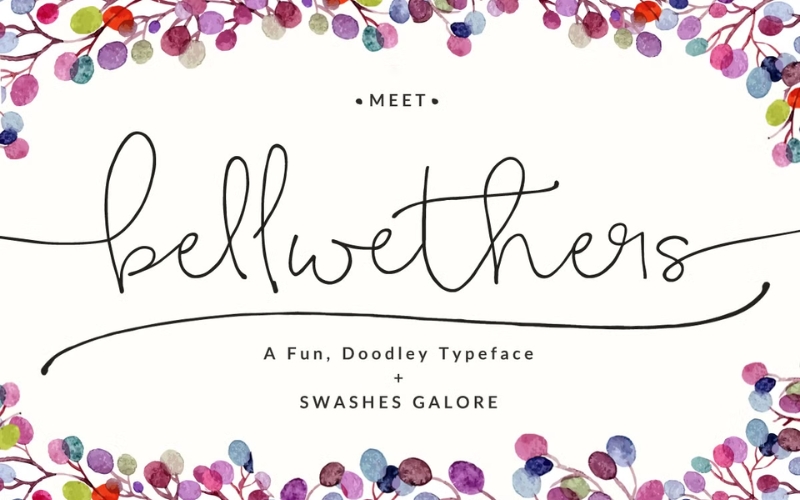
Việc sử dụng các font chữ đẹp và chuẩn Unicode đóng vai trò quan trọng trong thiết kế đồ họa, soạn thảo văn bản hay các ấn phẩm truyền thông. Trong số đó, bộ font SVN Việt hóa được nhiều người ưa chuộng nhờ tính thẩm mỹ cao và khả năng hỗ trợ đầy đủ tiếng Việt. Nếu bạn đang tìm kiếm cách tải font chữ SVN Việt hóa nhanh chóng và an toàn, bài viết dưới đây của Vietkey sẽ cung cấp đầy đủ link download miễn phí cùng hướng dẫn cài đặt chi tiết để bạn có thể sử dụng ngay trên máy tính của mình.
Font SVN Việt hóa là gì?
SVN Font là bộ font chữ đã được Việt hóa bởi một designer vào năm 2013, ban đầu chỉ thực hiện trên một số bộ font nhỏ và chia sẻ miễn phí trong cộng đồng designer. Nhờ sự ủng hộ nhiệt tình từ người dùng, nhu cầu sử dụng các font chữ đẹp, tiện lợi ngày càng tăng, designer này đã tiếp tục Việt hóa thêm nhiều bộ font khác.
Song song với đó, một số mẫu SVN font chất lượng cao được cung cấp dưới dạng dịch vụ trả phí, giúp designer vừa mang đến sản phẩm tốt vừa tạo nguồn thu nhập cá nhân. Những bộ font từ dự án này sau đó được gắn thương hiệu riêng là STYLEno.1 Fonts và nhận được sự tin tưởng, hài lòng từ đông đảo cộng đồng người dùng.
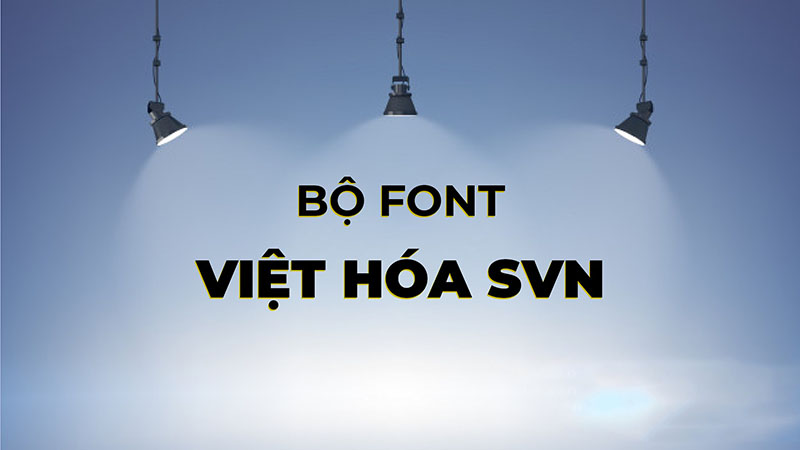
Tất cả các bộ font SVN Việt hóa đều sử dụng bảng mã Unicode phổ biến, đảm bảo khả năng tương thích cao với mọi phần mềm và thiết bị. STYLEno.1 Fonts phân chia SVN Font thành 5 nhóm chính gồm Script, Brush+Handwriting, Sans-serif, Serif+Slab và Others, mỗi nhóm mang đặc trưng riêng phù hợp với nhiều mục đích sử dụng khác nhau. Nếu bạn muốn sở hữu trọn bộ font đa dạng và tiện lợi, việc tải font SVN Việt hóa về máy tính sẽ giúp bạn dễ dàng lựa chọn các mẫu font phù hợp cho từng dự án thiết kế, soạn thảo hay sáng tạo nội dung.
Đặc điểm của bộ font chữ SVN Việt hóa
Bộ font chữ SVN Việt hóa được ưa chuộng nhờ sự kết hợp giữa tính thẩm mỹ và khả năng ứng dụng linh hoạt, phù hợp với nhiều nhu cầu từ thiết kế đồ họa, soạn thảo văn bản đến sáng tạo nội dung. Khi tải font SVN Việt hóa, người dùng sẽ nhận được một hệ thống font đa dạng, dễ sử dụng và tương thích với hầu hết các phần mềm trên máy tính. Dưới đây là những đặc điểm nổi bật của bộ font này:
- Hỗ trợ đầy đủ tiếng Việt: Toàn bộ các ký tự, dấu câu và chữ có dấu tiếng Việt đều được Việt hóa chuẩn xác, giúp việc soạn thảo và thiết kế trở nên thuận tiện.
- Đa dạng phong cách: SVN Font được chia thành nhiều nhóm như Script, Brush+Handwriting, Sans-serif, Serif+Slab và Others, đáp ứng các nhu cầu từ văn bản nghiêm túc đến sáng tạo nghệ thuật.
- Tương thích cao với phần mềm: Sử dụng bảng mã Unicode, các font chữ dễ dàng tương thích với Microsoft Office, Photoshop, Illustrator, InDesign và nhiều ứng dụng khác.
- Chất lượng và độ nét tốt: Các font được thiết kế chi tiết, hiển thị rõ ràng ở nhiều kích thước khác nhau mà không bị vỡ nét hay mất thẩm mỹ.
- Cập nhật thường xuyên: Bộ font liên tục được cập nhật để bổ sung thêm các mẫu mới, đảm bảo người dùng luôn có nhiều lựa chọn phong phú.
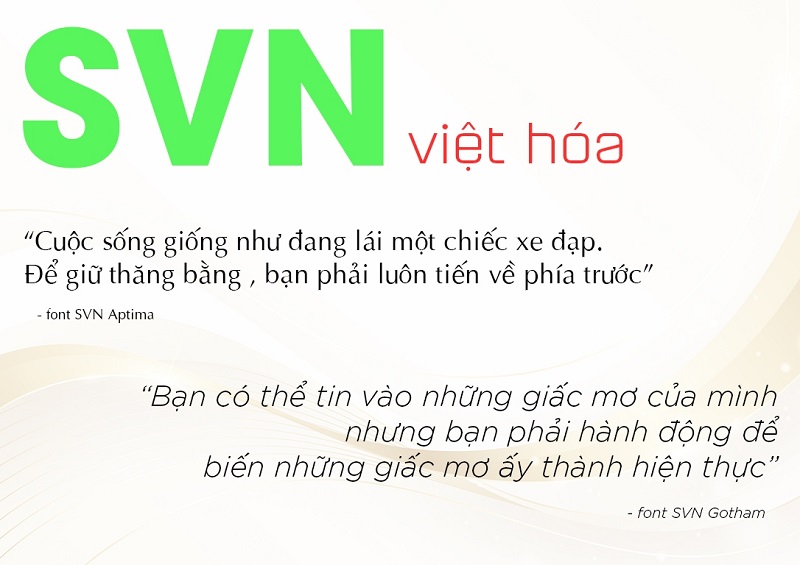
Các font SVN Việt hóa đẹp và thông dụng hiện nay
Trong cộng đồng designer và người dùng cá nhân, có rất nhiều bộ SVN font Việt hóa được yêu thích nhờ tính thẩm mỹ và sự tiện dụng. Khi tải font SVN Việt hóa, bạn sẽ dễ dàng lựa chọn các mẫu phù hợp với nhiều phong cách thiết kế khác nhau. Dưới đây là những font chữ SVN Việt hóa đẹp và thông dụng hiện nay, được nhiều người đánh giá cao và sử dụng phổ biến:
Font SVN-Gotham
Bộ SVN-Gotham thuộc nhóm Sans-serif và hiện được cung cấp dưới dạng trả phí trên trang web của STYLEno.1 Fonts. Font này được lấy cảm hứng từ kiểu chữ đơn giản đặc trưng của Mỹ, thường xuất hiện trên các công trình đô thị như tường sơn, kính hay trần thạch cao, và được thiết kế bởi Tobias Frere-Jones.
Với cấu trúc cơ bản, vật liệu thiết kế chuyên biệt, SVN-Gotham mang đến những dòng chữ đơn giản nhưng cuốn hút, dễ sử dụng và không lỗi thời. Đây là một trong những bộ font thành công, vẫn được ưa chuộng và sử dụng rộng rãi qua nhiều thế hệ, đặc biệt trong các công trình kiến trúc và thiết kế hiện đại.
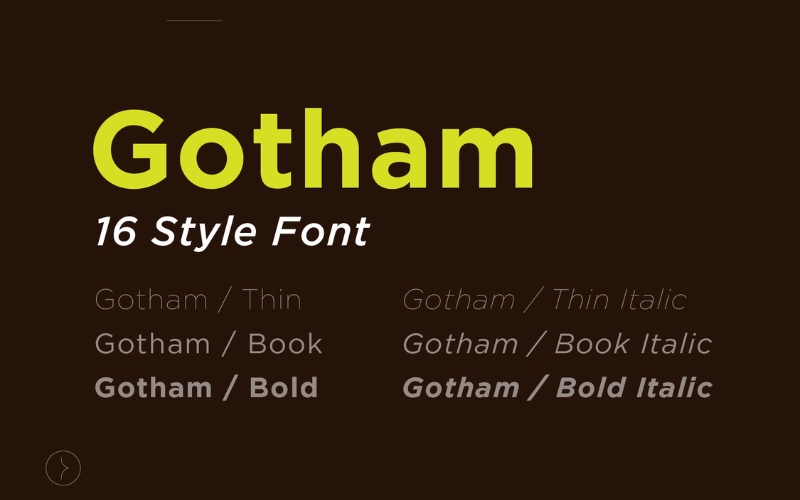
Font SVN-The Carpenter
Bộ SVN-The Carpenter thuộc kiểu Script và là lựa chọn phổ biến cho các thiết kế mang phong cách thanh lịch, đặc biệt là các dự án có chủ đề “Wedding”. Bạn có thể sử dụng phiên bản Việt hóa của bộ font này thông qua gói trả phí từ STYLEno.1 Fonts.
SVN-The Carpenter không chỉ cung cấp các ký tự cơ bản mà còn bao gồm nhiều hoa văn và kiểu chữ tượng hình, giúp thiết kế trở nên sinh động và tinh tế. Ngoài ra, bộ font còn cho phép tùy biến ký tự qua Glyph Palette, rất phù hợp để tạo headlines, banner, hay các mẫu logo đẹp, mang đến sự linh hoạt tối đa cho người dùng trong từng dự án sáng tạo.
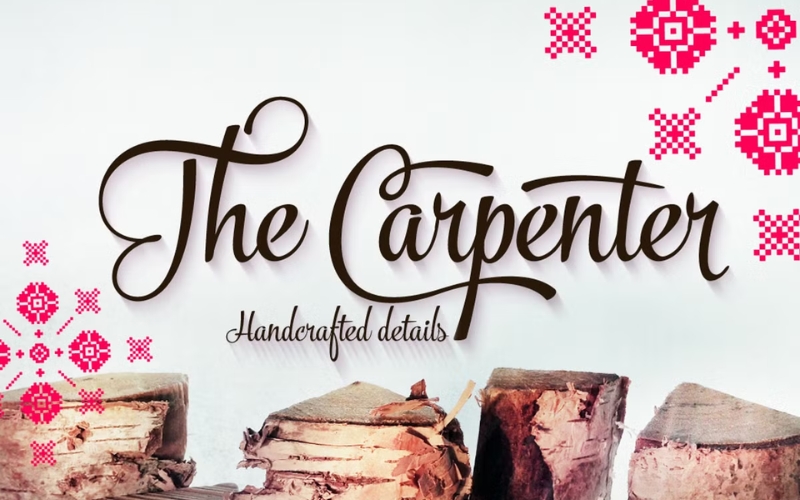
Font SVN-Gilroy
Bộ SVN-Gilroy thuộc kiểu Sans-serif hiện đại và được cung cấp dưới dạng trả phí bởi STYLEno.1 Fonts. Được thiết kế bởi Radomir Tinkov, font này mang phong cách đơn giản nhưng tinh tế, tương tự như bộ Gotham, đồng thời cung cấp nhiều tùy chọn linh hoạt để hỗ trợ người dùng trong quá trình thiết kế. SVN-Gilroy là lựa chọn lý tưởng cho các bảng hiệu công ty, doanh nghiệp, thiết kế website hay các ấn phẩm xuất bản, giúp sản phẩm của bạn vừa hiện đại vừa dễ đọc, đồng thời tạo điểm nhấn chuyên nghiệp và sang trọng.